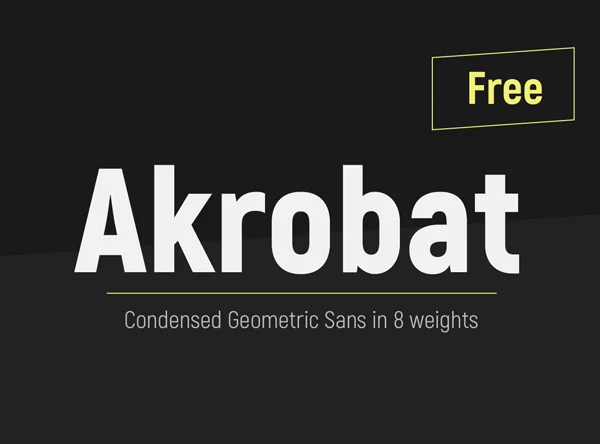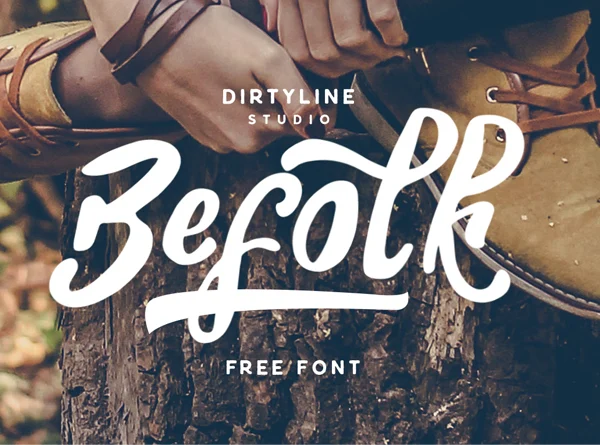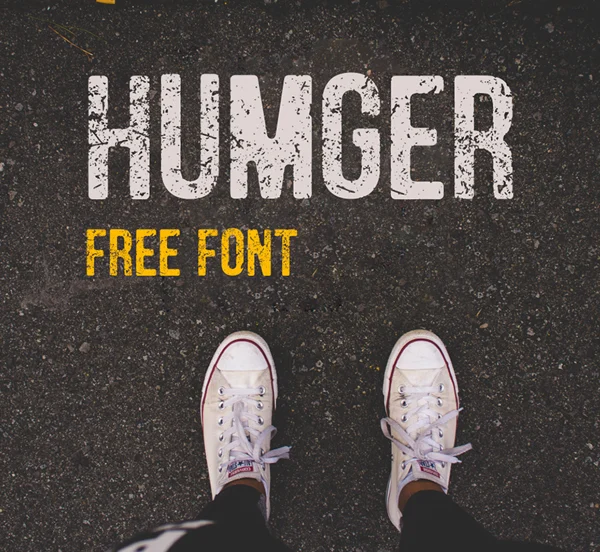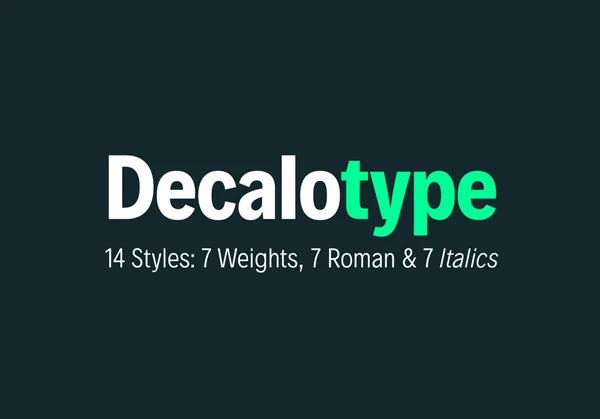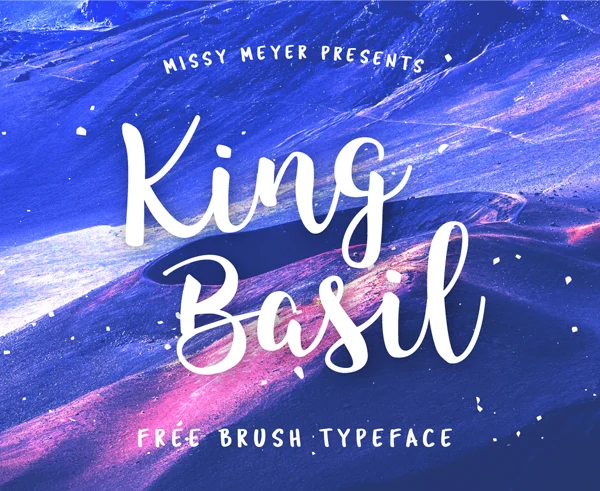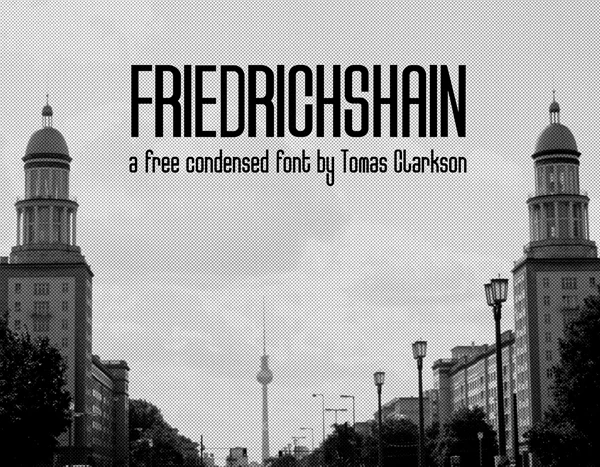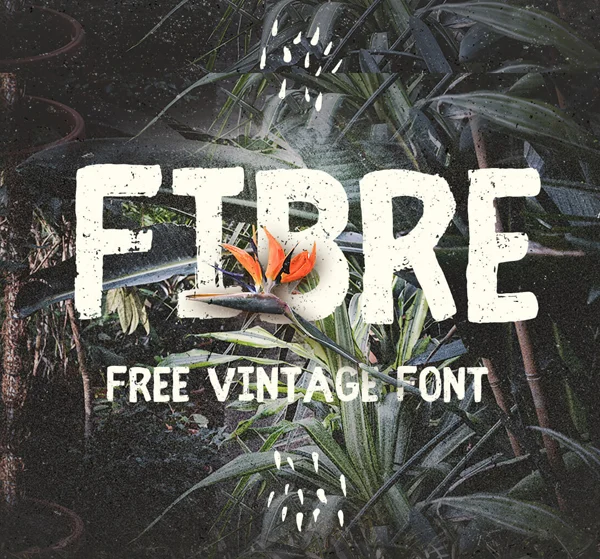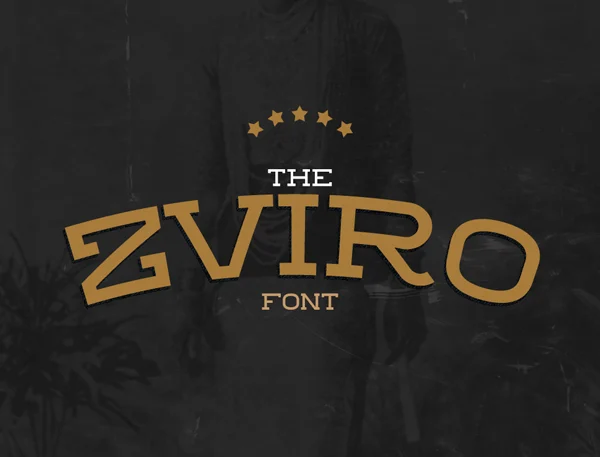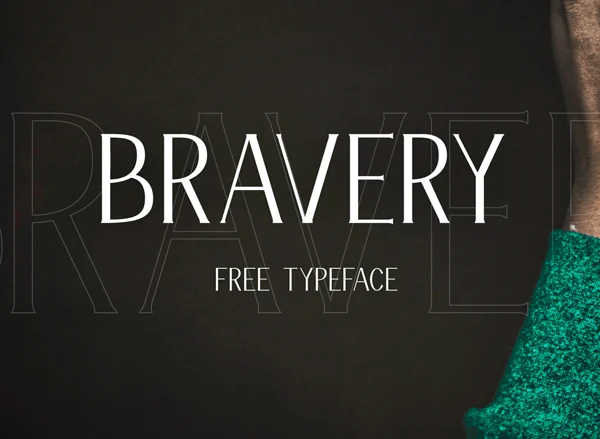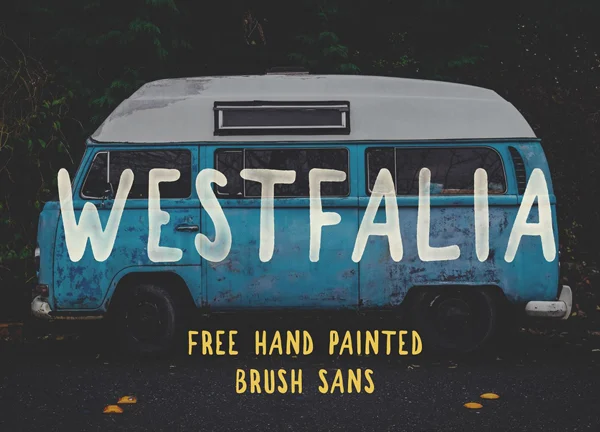
La typographie est bien plus qu’un moyen de rédiger quelque chose. C’est un moyen de mettre en forme ce que l’on souhaite dire et appuie le message qu’on veut partager. Lors du choix de la typographie, il faut bien réfléchir à ce que cette dernière signifie. Tout simplement car une typographie en baton ne voudra pas dire la même chose qu’une typographie en brush ou en « hand writing ».
Aujourd’hui, je vous propose une série de 10 typographies créatives qui devraient vous aider à rendre vos créations, vos publications ou même votre CV un poil plus élaboré. Car c’est bien beau d’utiliser de l’Arial ou de la Comic Sans MS, mais on bosse dans la communication et la direction artistique ne doit pas être laissée au hasard. Mais bon, je ne vous apprend rien car, si vous êtes sur Dans Ta Pub, c’est que vous avez déjà un minimum de bon goût 😎.
1 – Akrobat
2 – Befolk
3 – Humger
4 – Decalotype
5 – King Basil
6 – Friedrichshain
7 – Fibre
8 – Zviro
9 – Bravery
10 – Westfalia